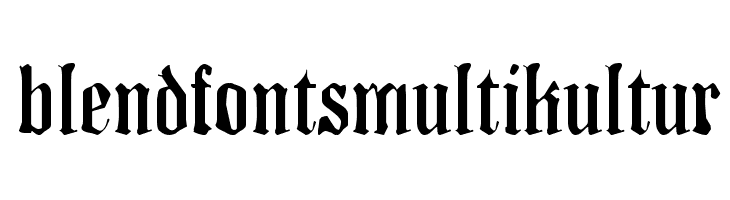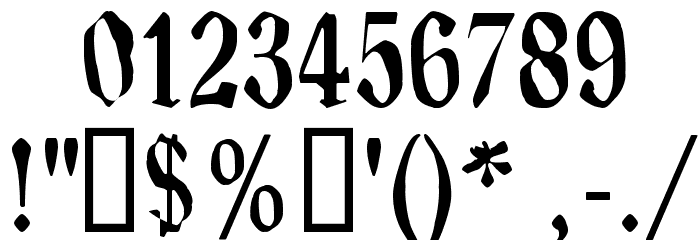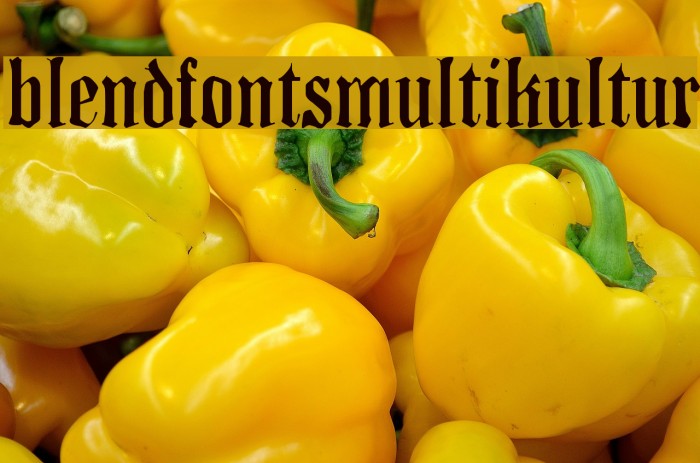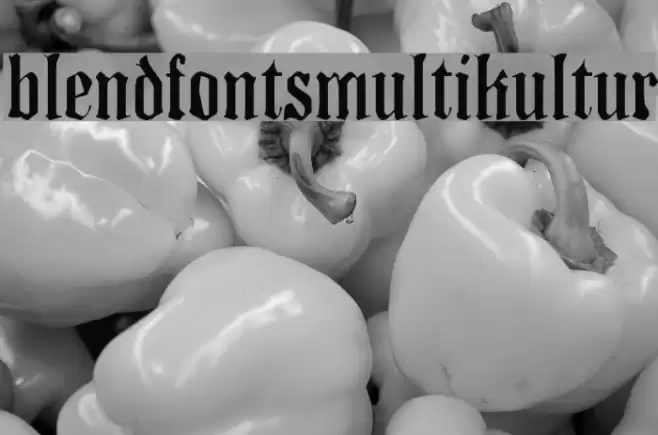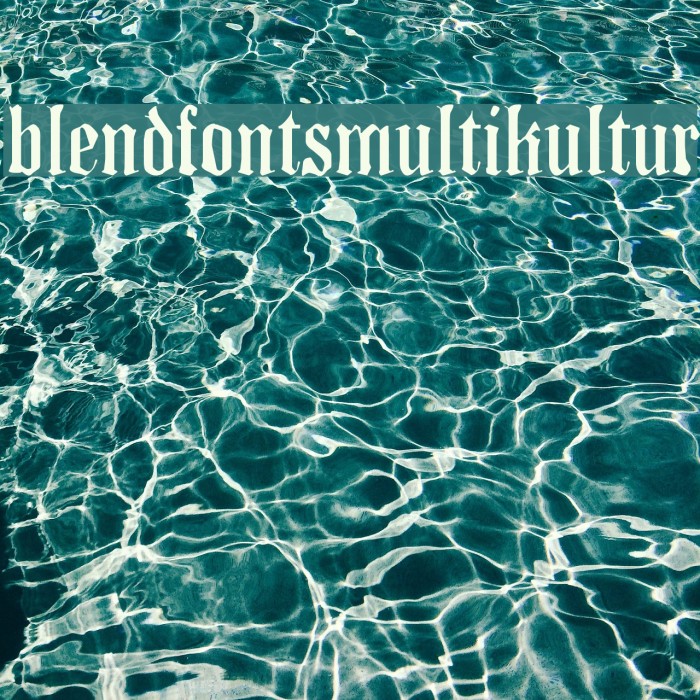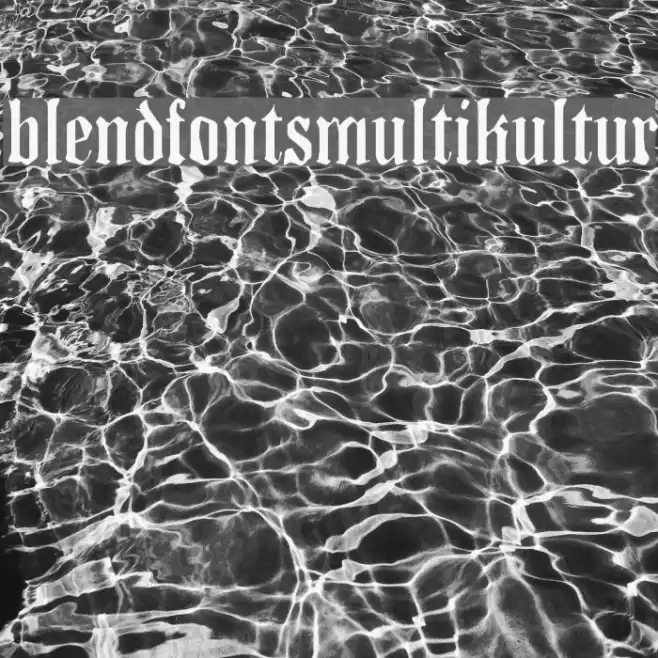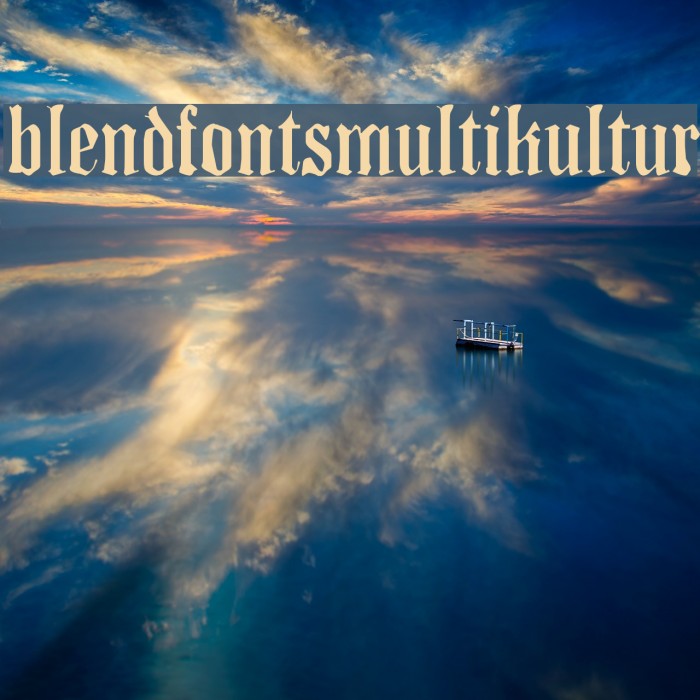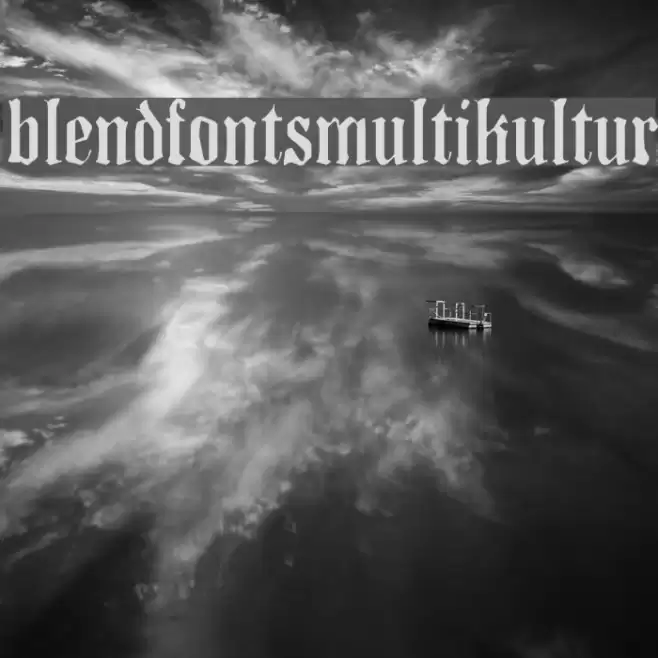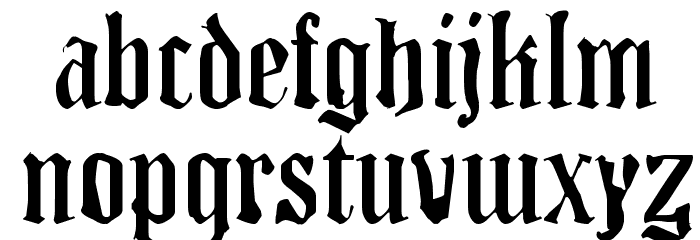
BlendfontsMultikultur Font
✎ Gothic
| 分类 | Gothic |
| 整体风格 | Vintage |
| 推荐项目 | Ideal for historical documents, vintage posters, book covers, and branding that requires a traditional or medieval touch. |